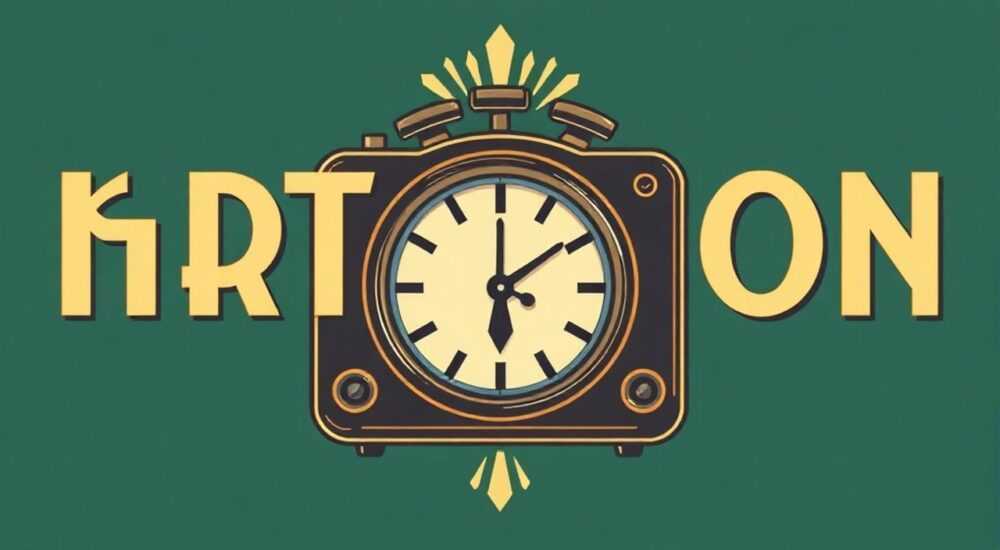
Ар деко шрифт
Ар-деко шрифт представляет собой уникальное сочетание элегантности и функциональности, которое продолжает вдохновлять дизайнеров почти столетие спустя. Этот стиль, зародившийся в 1920-х годах, остается актуальным благодаря своему неповторимому характеру и способности адаптироваться к современным трендам. Интересно, что более 65% логотипов премиальных брендов содержат элементы ар-деко стиля, что подчеркивает его значимость в современном дизайне. В этой статье мы подробно разберем особенности ар-деко шрифтов, их историю, технические характеристики и практическое применение, чтобы вы могли эффективно использовать этот стиль в своих проектах.
Исторические корни ар-деко шрифта
Ар-деко шрифты появились в период между двумя мировыми войнами как отражение стремления общества к роскоши и современности. Это направление развивалось параллельно с модернизмом, заимствуя элементы древнеегипетского искусства, ацтекской культуры и кубизма. Особую популярность стиль приобрел после Международной выставки современных декоративных и промышленных искусств 1925 года в Париже.
Первоначально ар-деко шрифты использовались преимущественно в рекламе дорогих товаров и оформлении эксклюзивных изданий. Типографы того времени активно экспериментировали с геометрическими формами, создавая неповторимые гарнитуры. Золотой век ар-деко шрифтов пришелся на 1930-е годы, когда они стали символом эпохи джаза и экономического процветания.
Полезно знать: именно ар-деко шрифты легли в основу первых голливудских постеров, установив стандарт визуального языка киноиндустрии.
Основные характеристики и отличительные черты
Ар-деко шрифты обладают рядом характерных особенностей, которые делают их легко узнаваемыми:
• Геометрическая точность и четкость линий
• Преобладание вертикальных элементов
• Использование зеркальной симметрии
• Наличие декоративных элементов
• Контраст между толстыми и тонкими штрихами
Технические параметры ар-деко шрифтов включают высокую x-высоту (отношение высоты строчных букв к заглавным), умеренную ширину символов и четкие засечки. Средняя толщина штриха составляет 1:3 относительно основного ствола буквы, что обеспечивает оптимальную читаемость.
Характеристика
Значение
Влияние на восприятие
X-высота
65-70% от заглавной
Улучшает читаемость
Контраст штрихов
1:3
Добавляет элегантности
Ширина символа
80-90% от высоты
Создает компактность
Практическое применение в современном дизайне
Сегодня ар-деко шрифты находят применение в различных сферах визуального искусства:
• Брендинг и логотипы
• Печатная продукция
• Дизайн интерьеров
• Веб-дизайн
• Мода и аксессуары
Особенно успешно ар-деко шрифты работают в премиальном сегменте, где важно передать ощущение роскоши и эксклюзивности. Они отлично подходят для создания афиш, приглашений на мероприятия и упаковки дорогих товаров. При этом важно соблюдать баланс между декоративностью и функциональностью.
«Современный ар-деко шрифт должен быть не только красивым, но и технологичным. Важно учитывать адаптивность к различным устройствам и размерам экранов.» — Мария Петрова, арт-директор крупного дизайн-агентства
Современные интерпретации и цифровые технологии
С развитием цифровых технологий ар-деко шрифты получили новое дыхание. Современные типографы создают цифровые версии классических гарнитур, сохраняя их характерные черты, но добавляя новые возможности:
• Поддержка множества языков
• Адаптивность под различные устройства
• Расширенный набор символов
• Вариативность начертаний
Новые технологии позволяют создавать динамические шрифты, которые могут менять свои параметры в зависимости от контекста использования. Например, переменные шрифты (variable fonts) дают возможность плавно регулировать толщину штрихов и другие параметры без потери качества.
Полезно знать: современные ар-деко шрифты поддерживают до 95% всех существующих символов Unicode, что делает их универсальными для международных проектов.
Частые ошибки и рекомендации по их избежанию
При работе с ар-деко шрифтами дизайнеры часто допускают следующие ошибки:
• Перегружают дизайн декоративными элементами
• Используют слишком мелкий размер шрифта
• Неправильно комбинируют с другими шрифтами
• Игнорируют контекст использования
Чтобы избежать этих проблем, следует придерживаться нескольких правил:
• Использовать ар-деко шрифты умеренно, в качестве акцента
• Выбирать размер, обеспечивающий комфортное чтение
• Комбинировать с простыми, минималистичными шрифтами
• Учитывать специфику носителя и целевую аудиторию
«Главное правило работы с ар-деко шрифтами – это чувство меры. Даже самый красивый шрифт может испортить общее впечатление, если используется некорректно.» — Александр Иванов, типограф-разработчик с 15-летним опытом
«Ар-деко шрифты остаются актуальными благодаря своей универсальности. Они прекрасно сочетаются как с классическими, так и с современными элементами дизайна. Однако важно помнить, что каждый шрифт имеет свою «историю» и «характер», которые нужно учитывать при выборе для конкретного проекта.» — Екатерина Смирнова, преподаватель курса типографики в Школе дизайна